Bộ Font thư pháp
Bộ font thư pháp là font chữ tiếng Việt phong cách thư pháp vô cùng độc đáo. Với Bộ font thư pháp bạn có thể tự mình tạo ra những câu đối ngày Tết giống như Ông
Bộ Font thư pháp là font chữ tiếng Việt thư pháp nghệ thuật miễn phí để viết câu đối ngày Tết như một Ông Đồ chuyên nghiệp. Với Bộ Font thư pháp bạn có thể thoải mái sáng tạo ra nhưng câu đối mang phong cách riêng biệt của mình hoặc tạo ra những hình ảnh lồng ghép chữ đầy thú vị và độc đáo.
Lưu ý: Trên Word các font chữ thư pháp hiển thị trên trang văn bản sẽ không nhìn thấy phần chân của ký tự đối với các chữ: g, y, q vì nó dài hơn bình thường. Nhưng khi in ra thì hoàn toàn chính xác, các bạn hoàn toàn yên tâm nhé.
Trong Bộ font thư pháp có rất nhiều mẫu chữ thư pháo khác nhau, bạn có thể thoái mái lựa chọn để tìm kiếm phong cách phù hợp nhất. Mỗi mẫu chữ đều được tạo ra vô cùng chỉn chu và bạn có thể cảm nhận được sự tinh tế đó qua từng nét chữ. Mỗi nét chữ thanh hay đậm trong mỗi font chữ đều được cân nhắc kỹ lưỡng để đạt đến giá trị nghệ thuật viết chữ đẹp cao nhất.
Đặc điểm của Bộ Font thư pháp
- Tính thẩm mỹ cao: Font chữ thư pháp có những đường nét mềm mại, uyển chuyển, tạo nên vẻ đẹp riêng biệt và lôi cuốn. Các nét thanh nét đậm được nhấn nhá có chủ đích, giúp thu hút sự chú ý và làm nổi bật các ấn phẩm.
- Khả năng truyền tải thông điệp: So với các font chữ thông thường, font chữ thư pháp có khả năng truyền tải thông điệp hiệu quả hơn. Các nét chữ thể hiện được cảm xúc và ý đồ của người thiết kế.
- Tính độc đáo và khác biệt: Mỗi font chữ thư pháp mang một vẻ đẹp riêng, thể hiện được phong cách và gu thẩm mỹ của người sáng tạo, giúp tăng tính cá nhân hóa và tạo dấu ấn riêng.
- Gợi cảm xúc và vẻ hoài cổ: Font chữ thư pháp thường có các nét uốn lượn, mềm mại như bút lông vẽ, tạo cảm giác hoài cổ, sang trọng, lãng mạn và dịu dàng.
- Đa dạng về kiểu chữ: Có rất nhiều kiểu chữ thư pháp khác nhau, cho phép người dùng tự do lựa chọn font chữ phù hợp với nội dung và mục tiêu của văn bản.
- Giống với nét viết tay: Font chữ thư pháp giúp cho những câu chữ trở nên chân thực hơn, giống như được viết tay bởi một "ông đồ" với những nét chữ tuyệt vời, dứt khoát và mạnh mẽ.
Thư pháp là một thuật ngữ dùng để chỉ loại hình Nghệ Thuật Viết Chữ Đẹp. Với định nghĩa như vậy thì thư pháp, trước hết phải được hiểu là một bộ môn nghệ thuật. Vì vậy sản phẩm của nó là tác phẩm nghệ thuật.
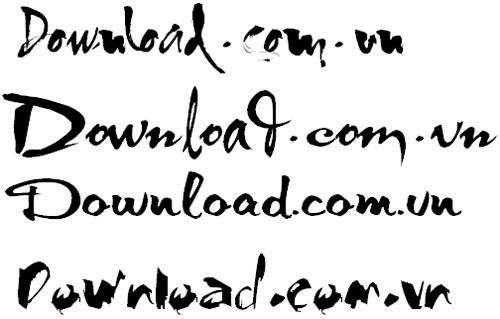
Câu hỏi thường gặp về Bộ font thư pháp
Font thư pháp là gì?
- Font thư pháp là kiểu chữ mô phỏng nét viết tay nghệ thuật, thường mang phong cách Á Đông, uốn lượn mềm mại, thể hiện sự cổ điển, trang trọng hoặc lãng mạn. Chúng thường được dùng trong các thiết kế Tết, thư pháp chữ Việt, thiệp, tranh câu đối, v.v.
Font thư pháp có hỗ trợ tiếng Việt không?
- Một số font có hỗ trợ tiếng Việt đầy đủ (bao gồm cả dấu và ký tự đặc biệt như Ă, Â, Đ, Ê...), tuy nhiên cũng có những font thư pháp chỉ hỗ trợ tiếng Anh hoặc thiếu dấu tiếng Việt.